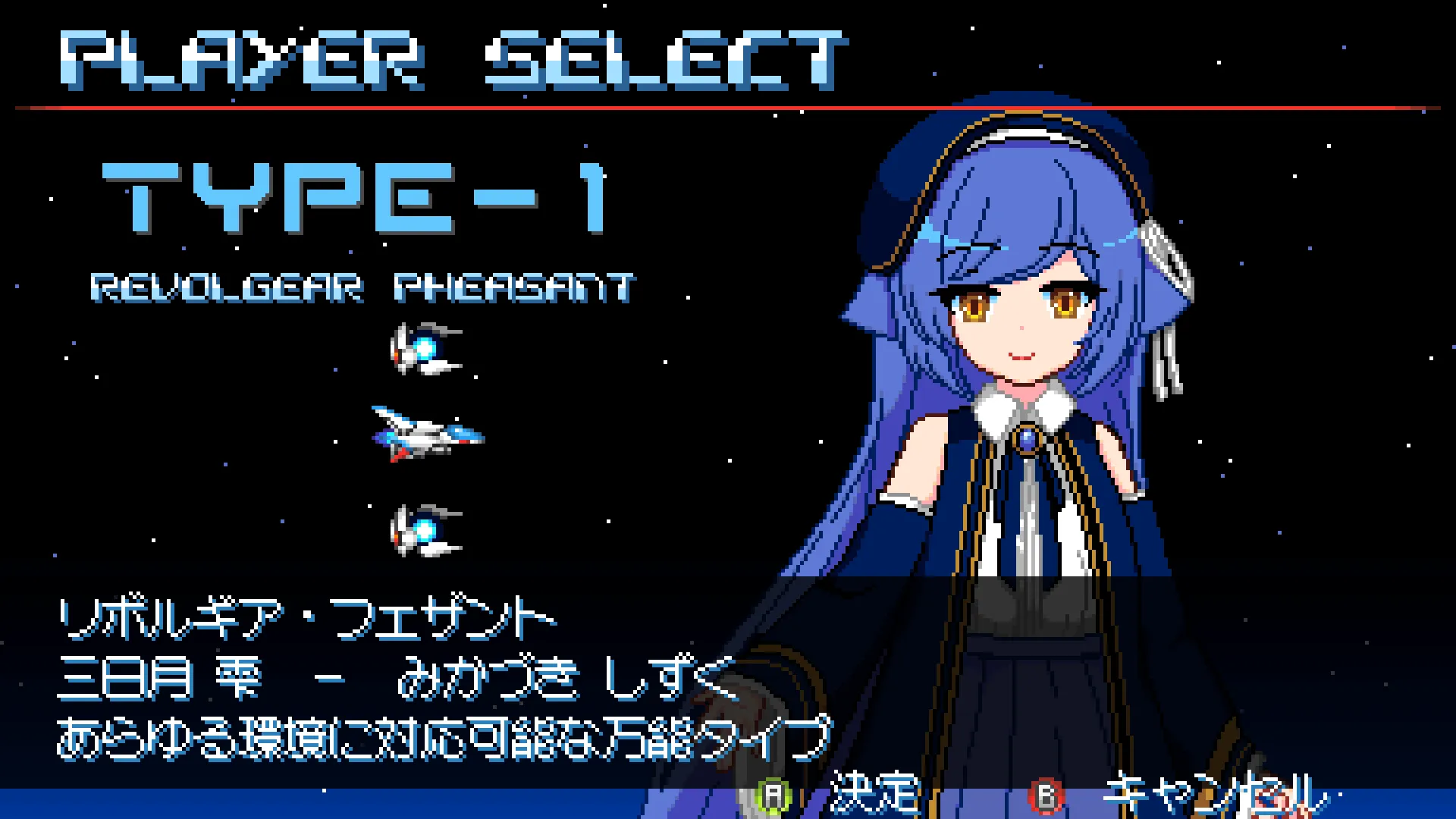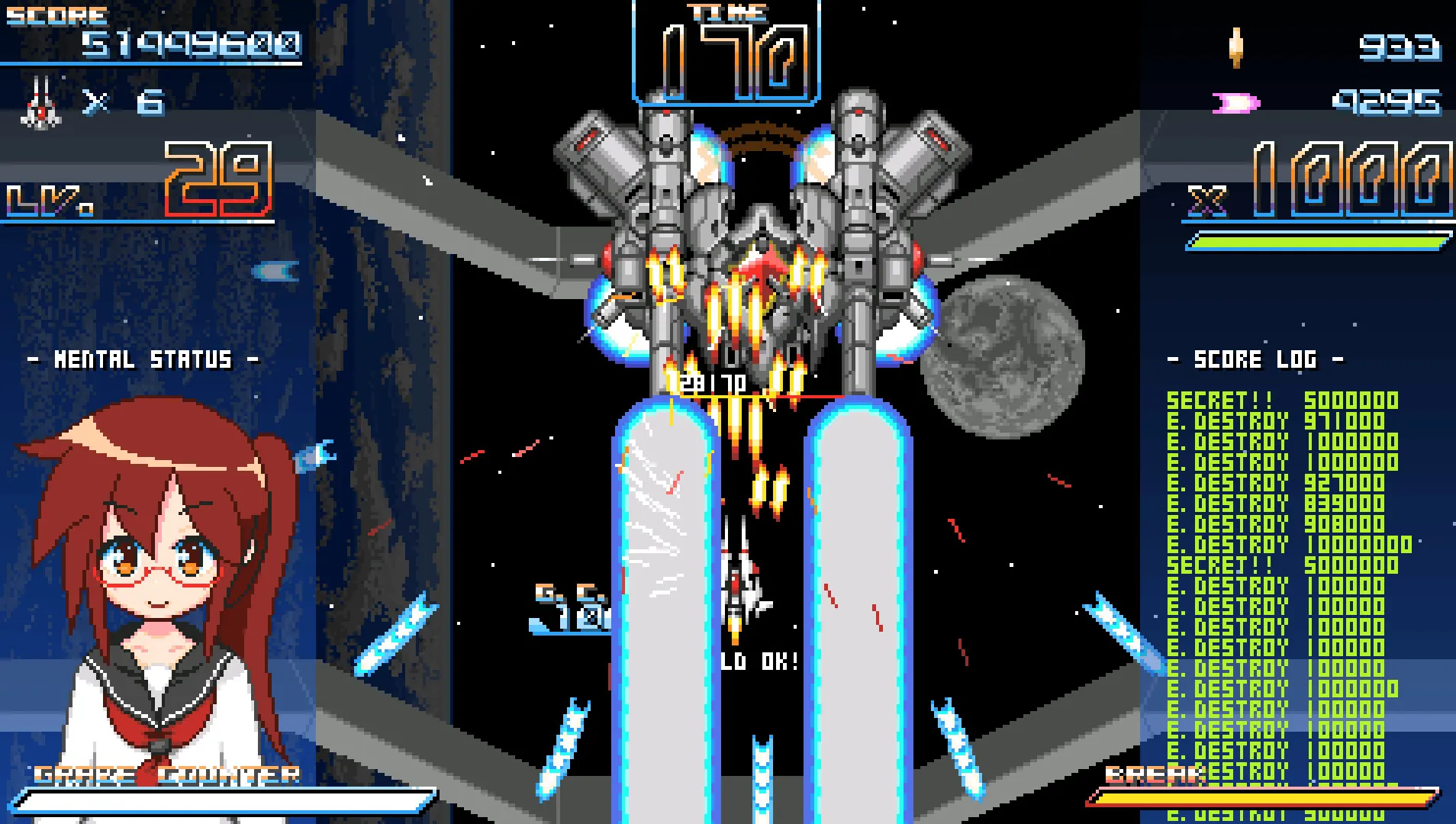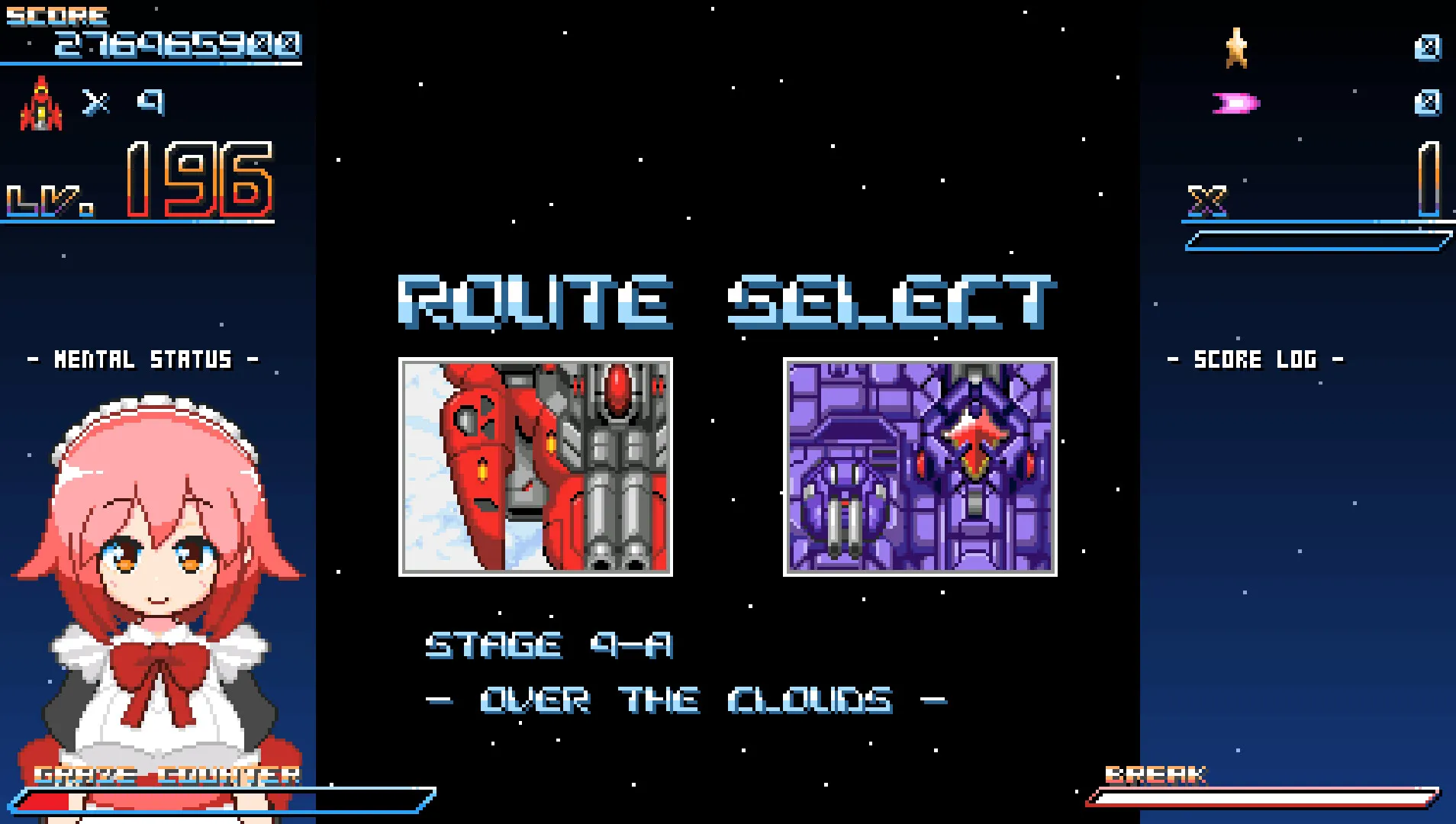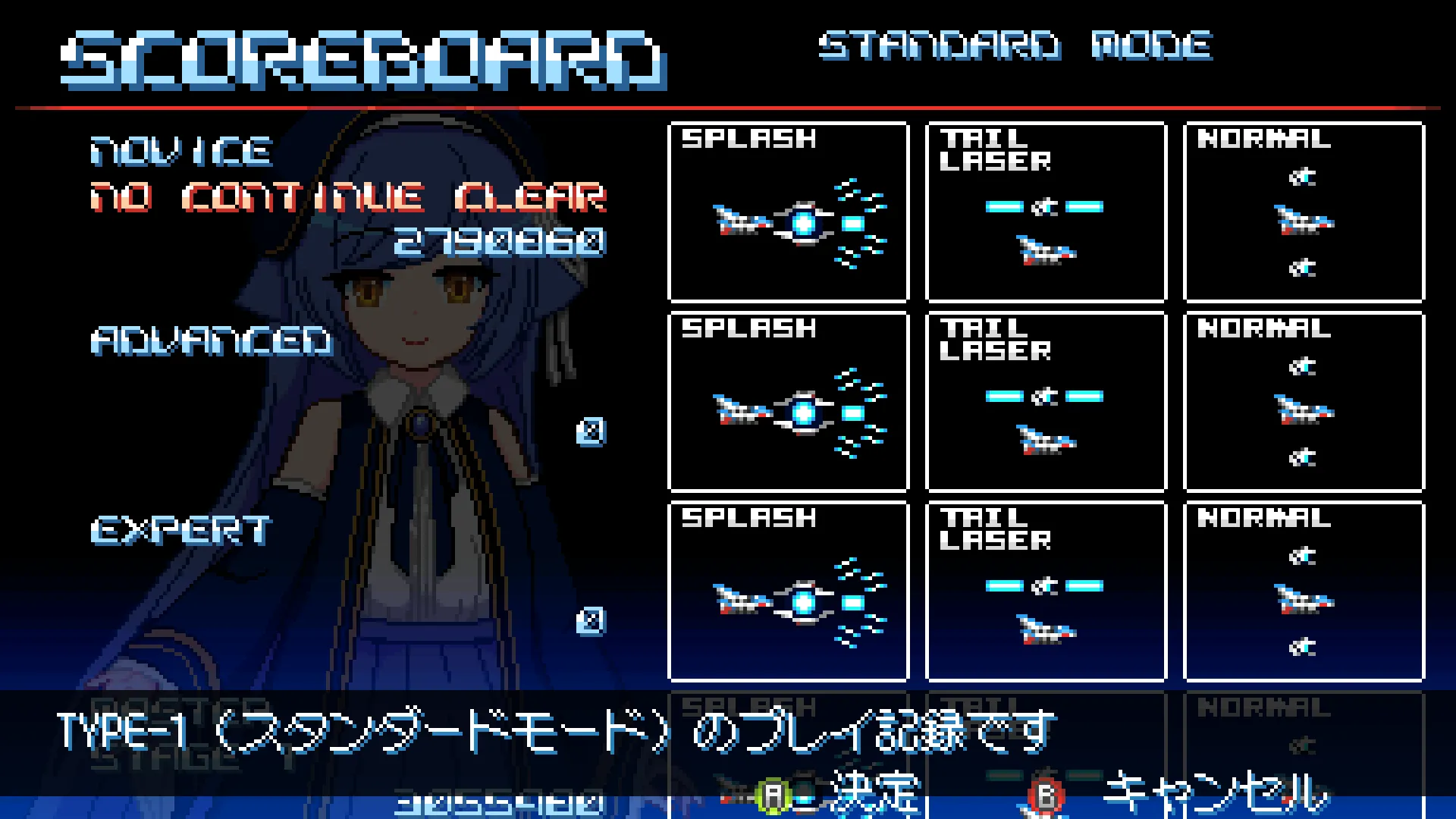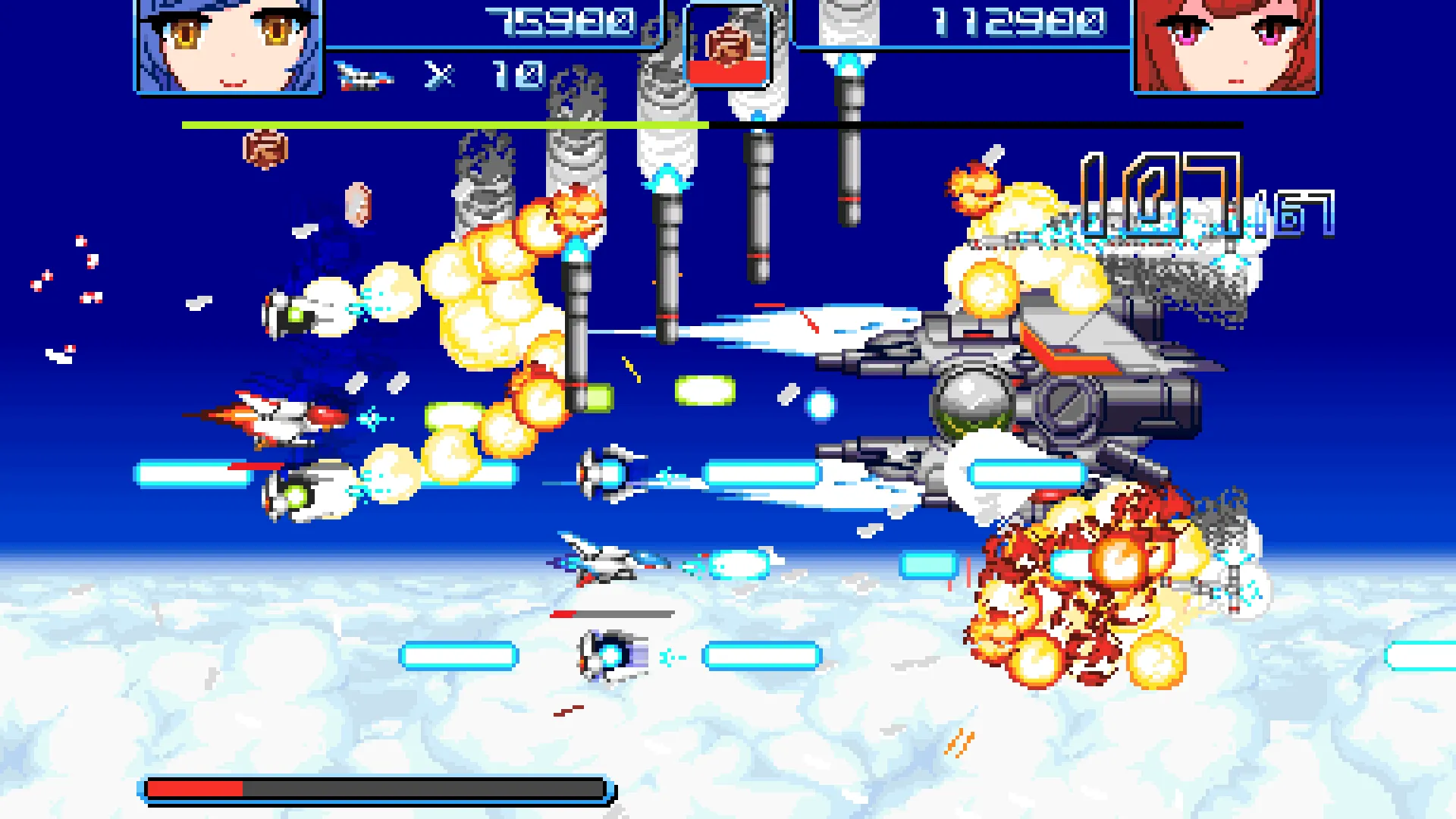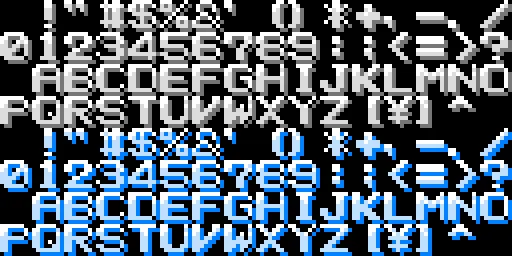
- 書体名: Revolties(リボルティーズ)1
- デザイナー: 白銀ねこび(びっくりソフトウェア代表)2
- 初出: 基本のシステムフォント(8x8)は Graze Counter GM(2023年1月19日発売)34、ネームエントリー用(16x12)は Revolgear Zero(2026年2月19日発売)31
Revolties は、びっくりソフトウェアのゲームで使われているシステムフォントのシリーズの名前で、用途ごとに「8x8」「16x24」のような大きさの違うものがある1。この記事で MICR 書体として取り上げるのは、基本のシステムフォントの 8x8 と、ネームエントリー用の 16x12。
ゲームの中では、水色(Blue)と赤(Red)の2色で使われている。
書体名は、2025年10月、筆者が情報提供を依頼したのをきっかけに付けられた。過去の作品のフォントにも、このとき暫定的に名前が付けられた15。
Graze Counter GM
敵の攻撃を自機にかすらせてゲージを溜め、レーザー兵器「グレイズカウンター」で敵を撃破していくシューティングゲーム。2017年の『Graze Counter』を、グラフィック・サウンド・システムを一新してマルチプラットフォームで出し直したもの3。
基本のシステムフォントに Revolties(8x8)が使われている。3作目の 8x8 の文字で、読みやすくし、文字の装飾を改良したもの1。
スコア倍率とボスタイマーには、大きな Revolties(16x24)が使われている。視認性を確保するため、中を空洞にしてある1。このほか、記号を多く加えた小さな Revolties(4x6)があり、色を変えたものは敵を撃破したときのログの表示に使われている1。
Revolgear Zero
ドット絵とボイス付きのキャラクターが特徴の横スクロールシューティングゲーム。自機は48種類の武器から装備を選べ、2人同時プレイもできる3。
基本のシステムフォントは Graze Counter GM と同じ Revolties(8x8)だが、プログラムの都合で記号の一部をアイコンに置き換えている。スタッフロールを正確に表示するため、記号も一部追加している1。
新しく作られたのは、ネームエントリー用の Revolties(16x12)と、ボス戦の前に出る「SHOOT!!」用の Revolties(12x6)。12x6 は、当初はネームエントリー用として作ったもの1。
ボスタイマーには、Graze Counter GM に続いて Revolties(16x24)が使われている。武器の名前には、REVOLGEAR II から使われている Origin(6x6)が使われている1。
Revolties で表示できる文字は、今後広げる予定だという(2026年9月現在)1。
日本語と英語のメッセージには「マルミーニャ」、中国語のメッセージには「Zpix」が使われている2。
それ以前のシステムフォント
フォントは作品の世界観を象徴するので、開発の初期にまずシステムフォントを作るという6。びっくりソフトウェアは、作品ごとにシステムフォントを作り、その都度改良したり文字を足したりしてきた4。基本のシステムフォントが MICR 書体になったのは Graze Counter GM からで、それ以前は次のようなフォントが使われていた1。
REVOLGEAR II(2012〜2013年)
基本のシステムフォントは Origin(オリジン)。既存の作品を参考に作ったもので、用途ごとに大きさと色を変えている1。
KIRISAME BLADE 1・2(2015年)
基本のシステムフォントは Kirisame(キリサメ)。8x8 は Origin を基に改良したもので、16x16 は 8x8 を滑らかにしたもの。このデザインが、後の作品の方針になった1。
Graze Counter(2017年)
基本のシステムフォントは Kirisame(8x8)で、U と V の区別が付かないので、部分的に改良している。Origin(6x6)も基本のシステムフォントとして使われている1。
Revolties の名前の付いたフォントは、この作品から使われている。スコア倍率とボスタイマー用の 16x24 は、視認性を確保するため中を空洞にしてある。撃破点の表示には 6x8、システムの説明の補助には 4x6 が使われている。4x6 は、似たフォントはよく見かけるが、この用途のためにデザインしたもの1。